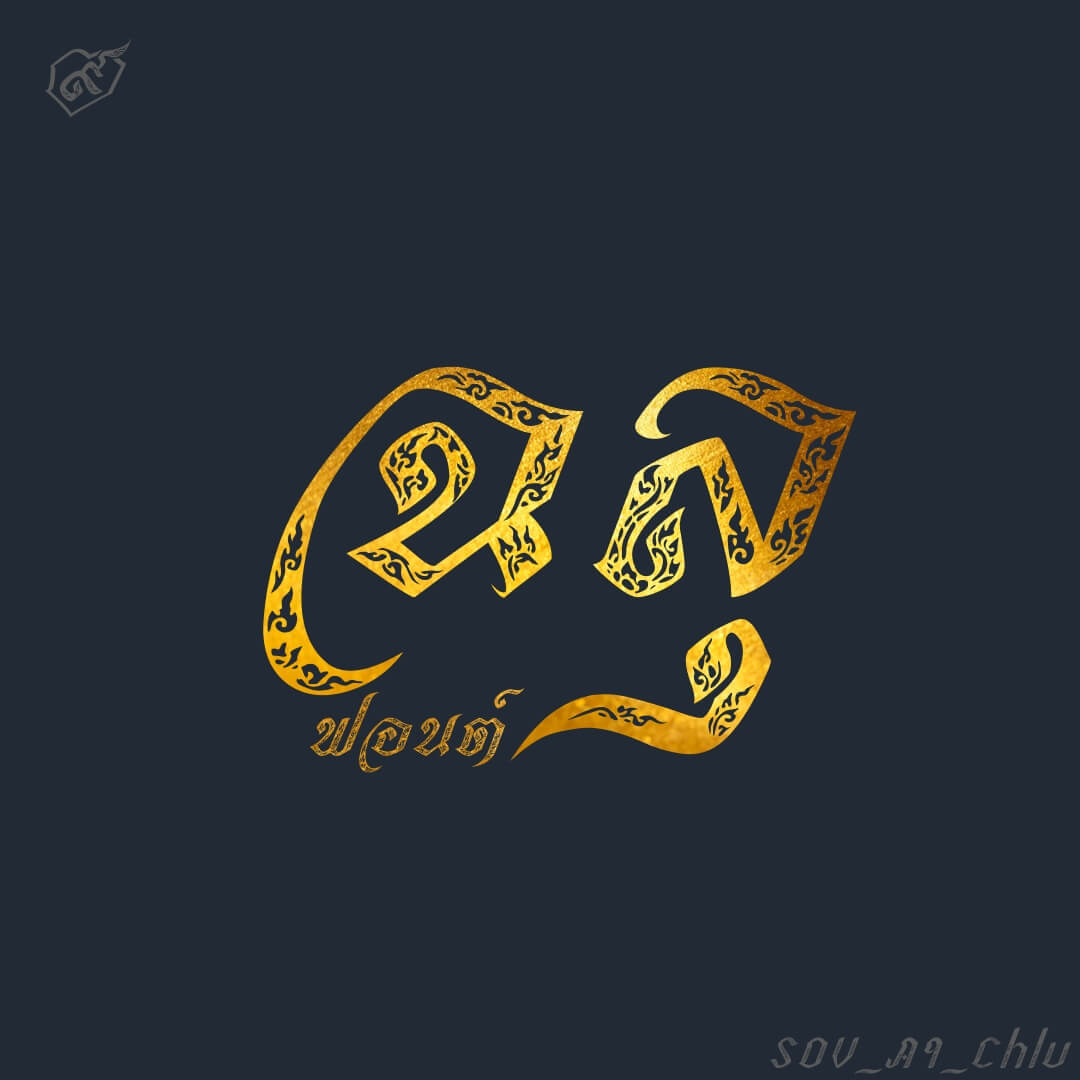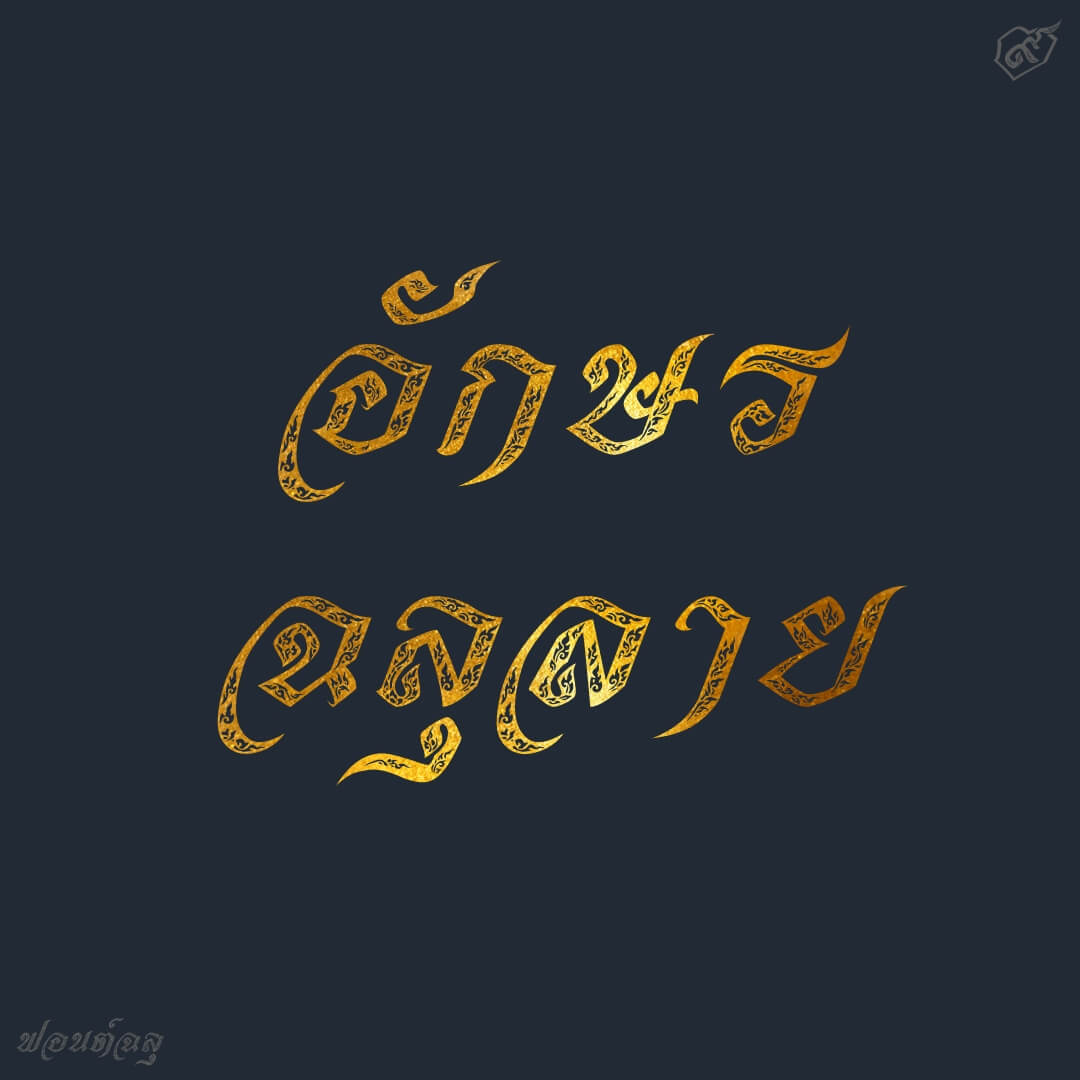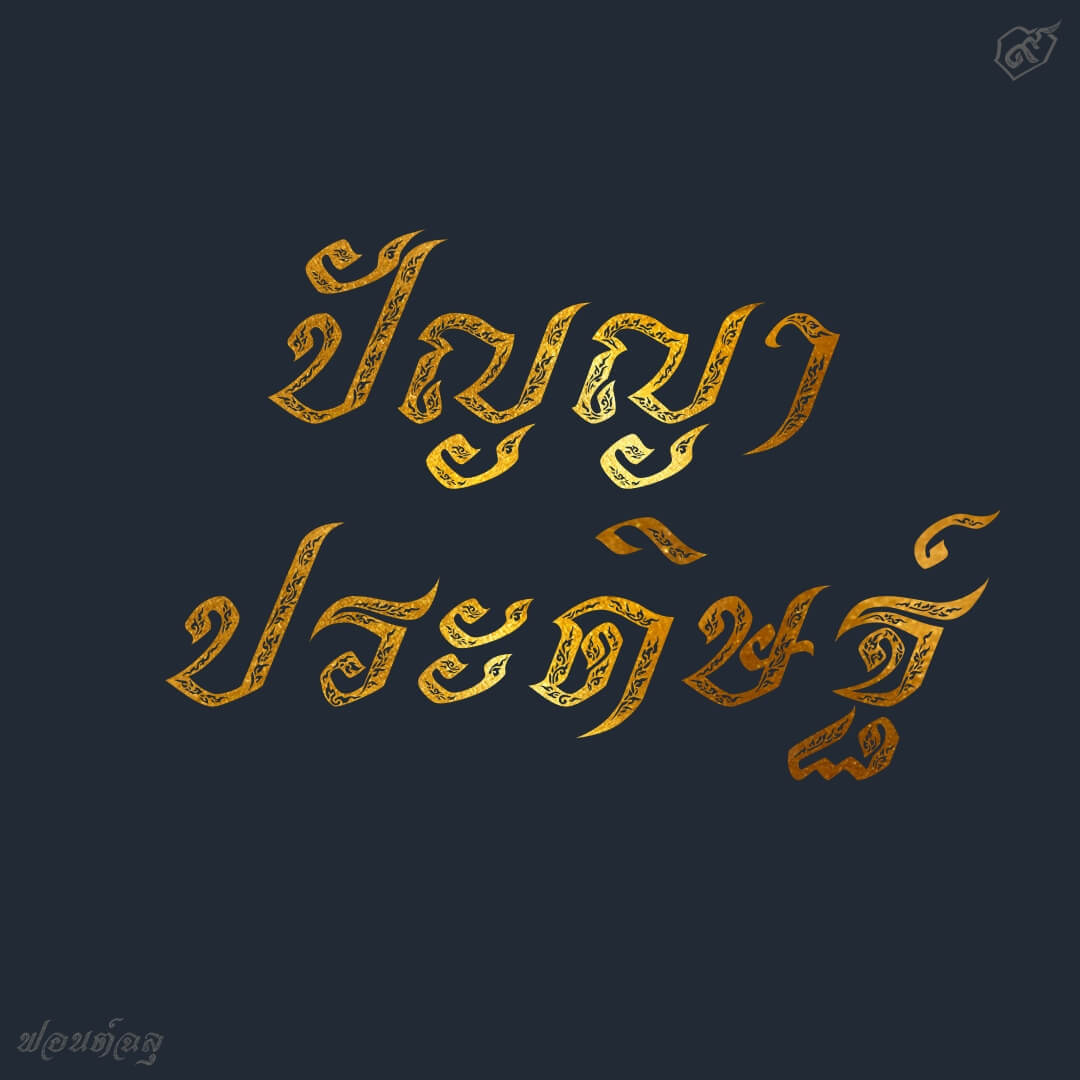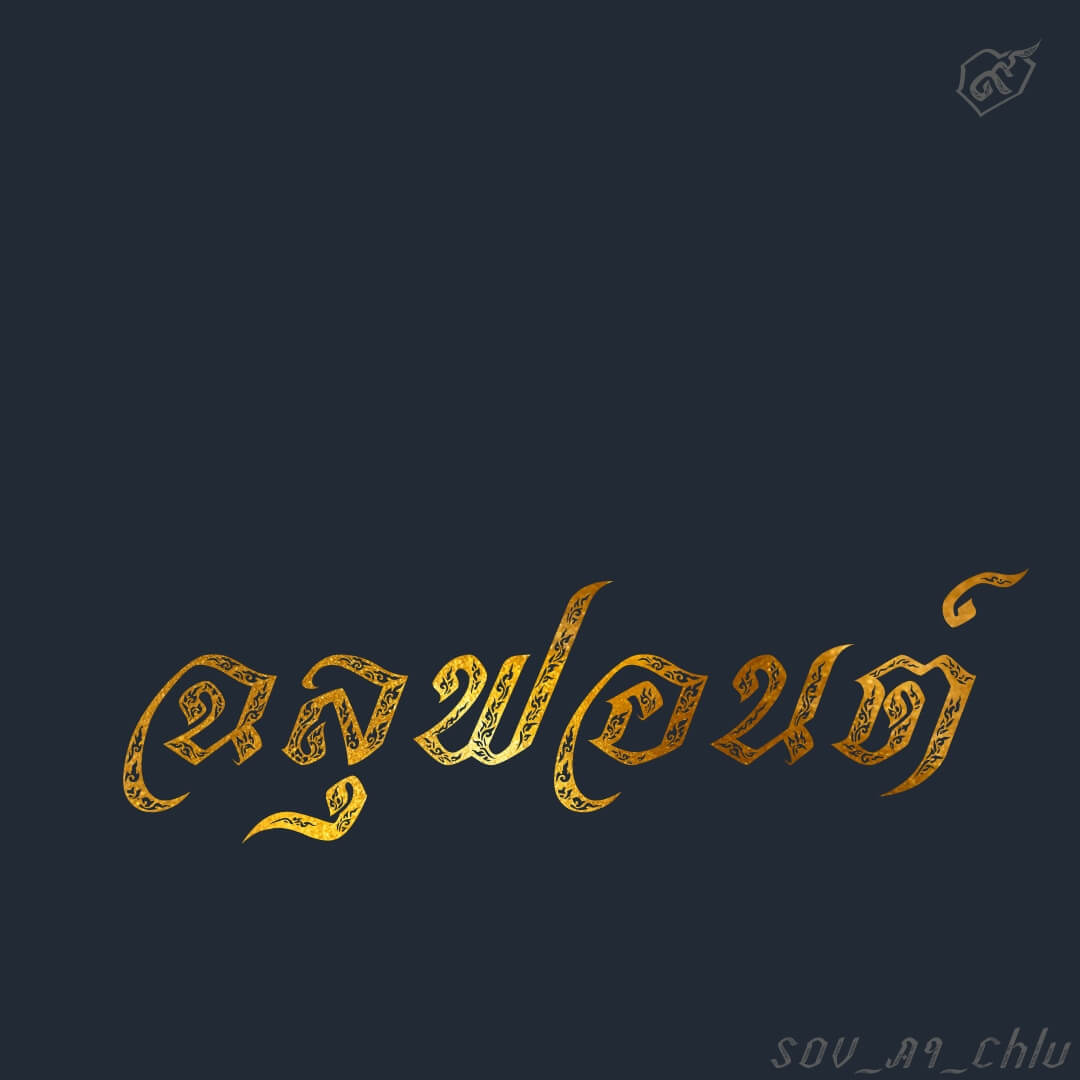
ฉลุ – เป็นฟอนต์ทำลองนำ AI มาช่วยออกแบบลาย บนฟอนต์เดิมของเรา… ตะแบงเอียง (SOV_TaBang) แล้วนำลายนั้น ย้อนกลับมาทำเป็นลายฉลุบนฟอนต์อีกที
เบื้องหลังการออกแบบ : ฟอนต์ ฉลุ
ฉลุ (SOV_AI_Chlu)